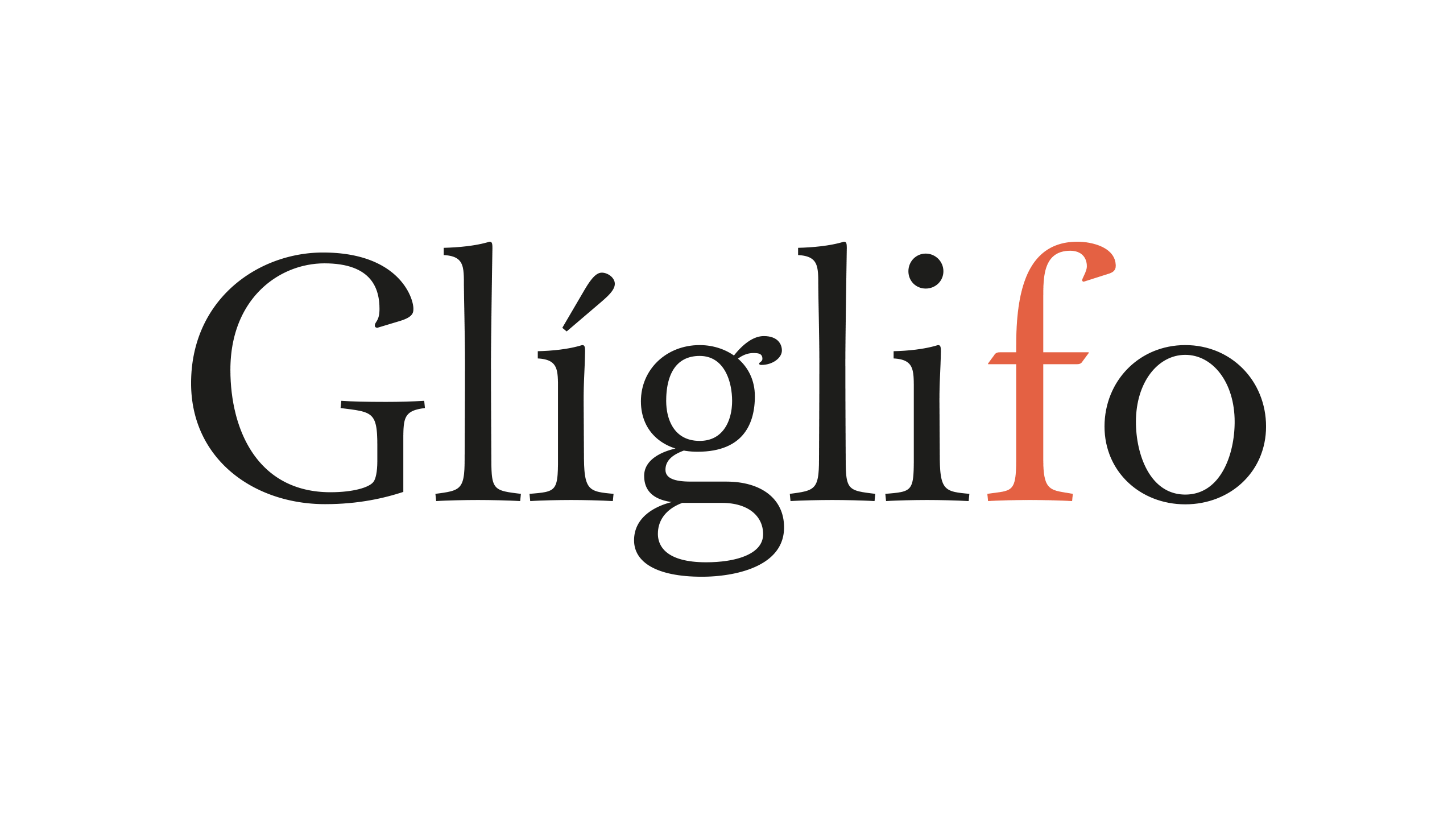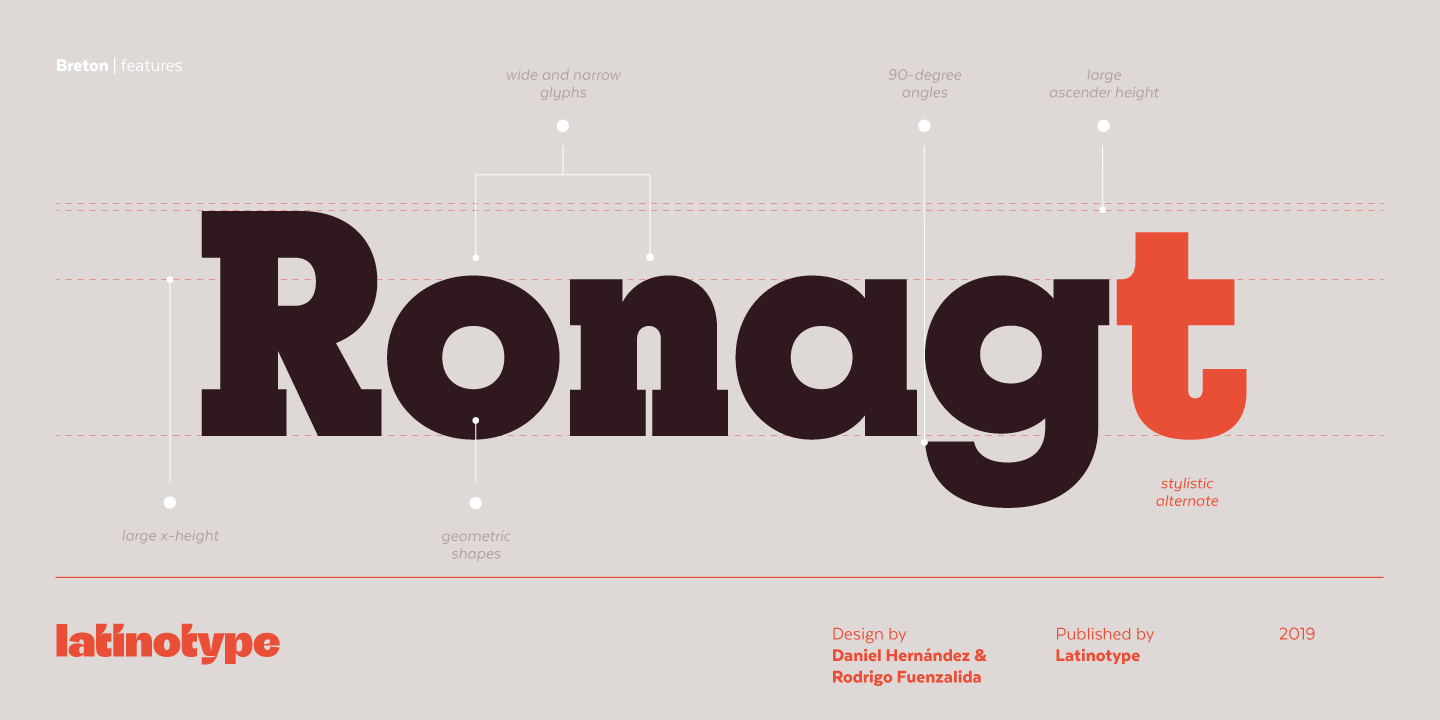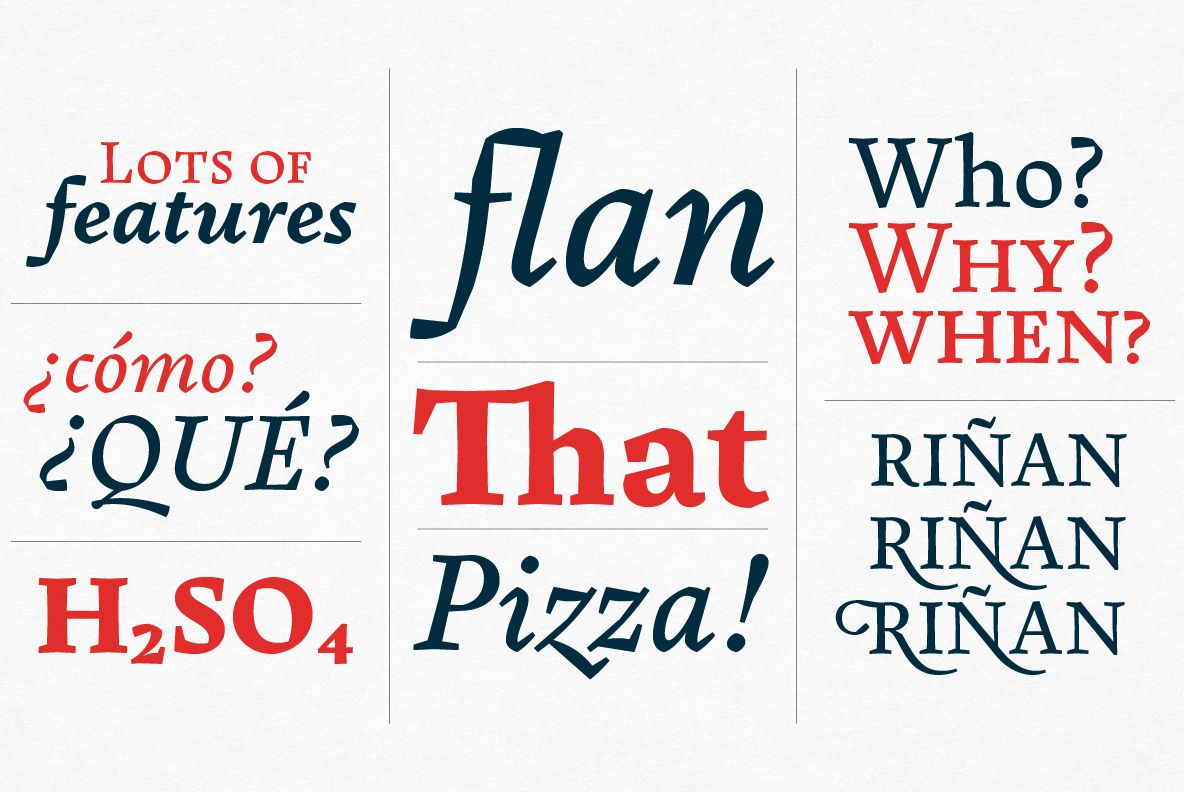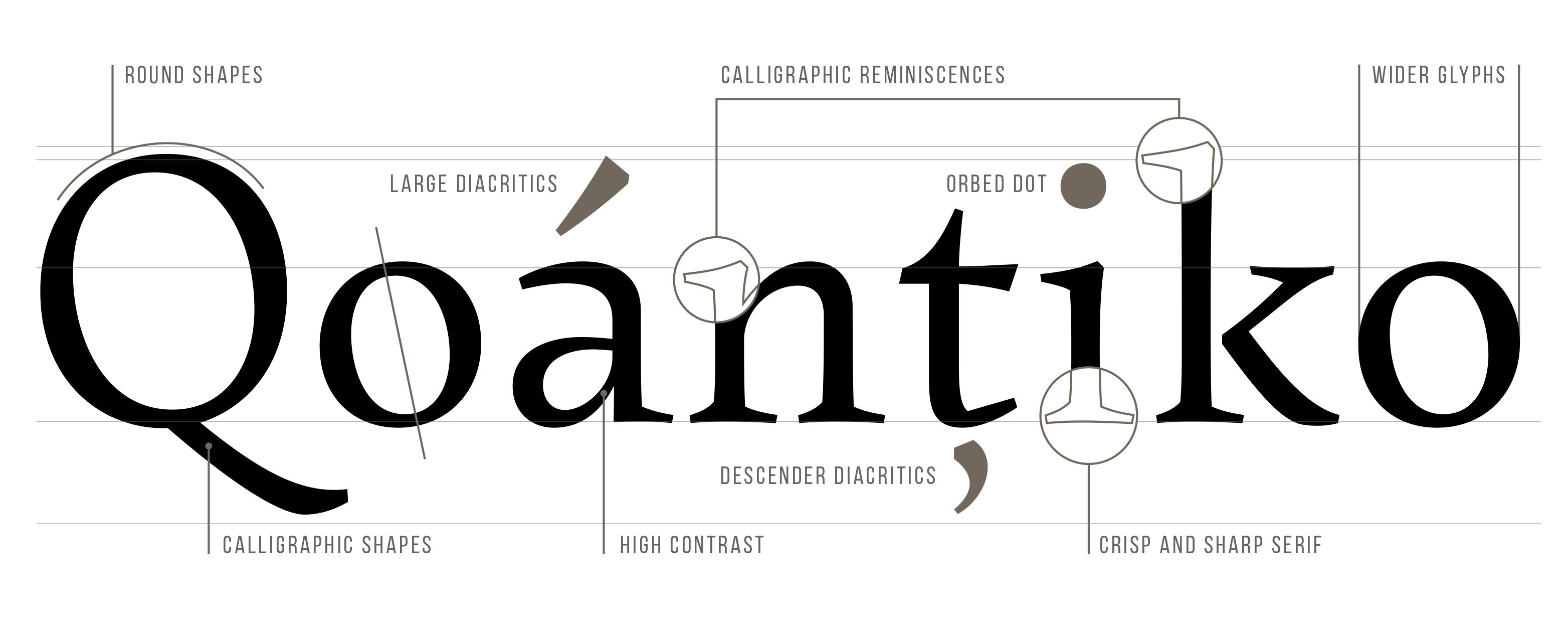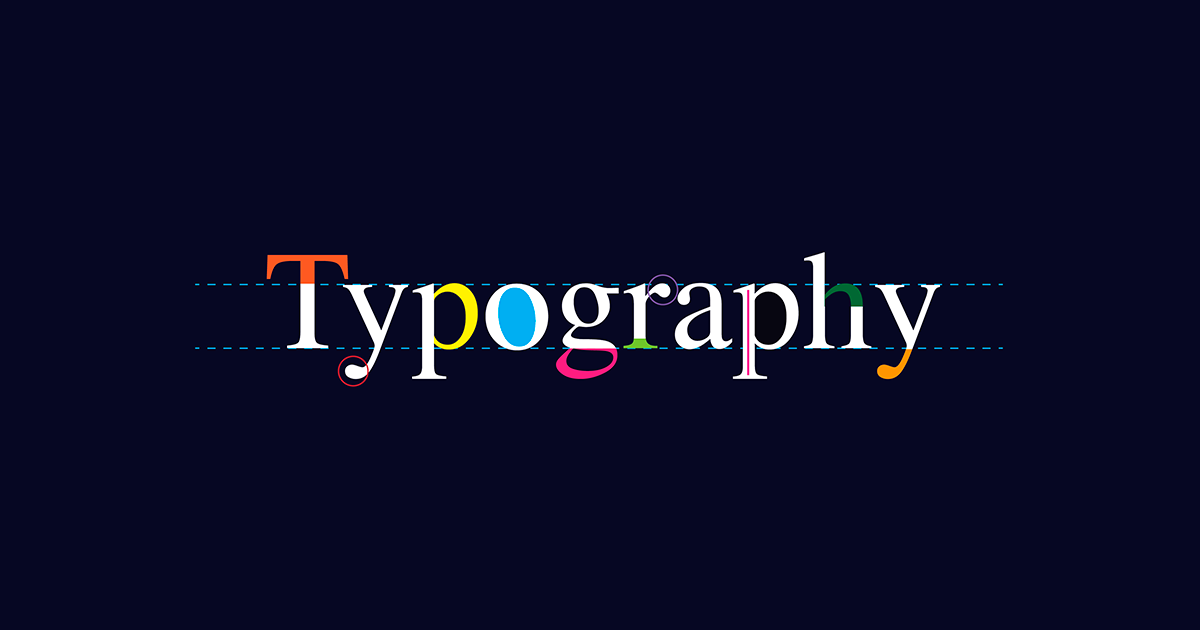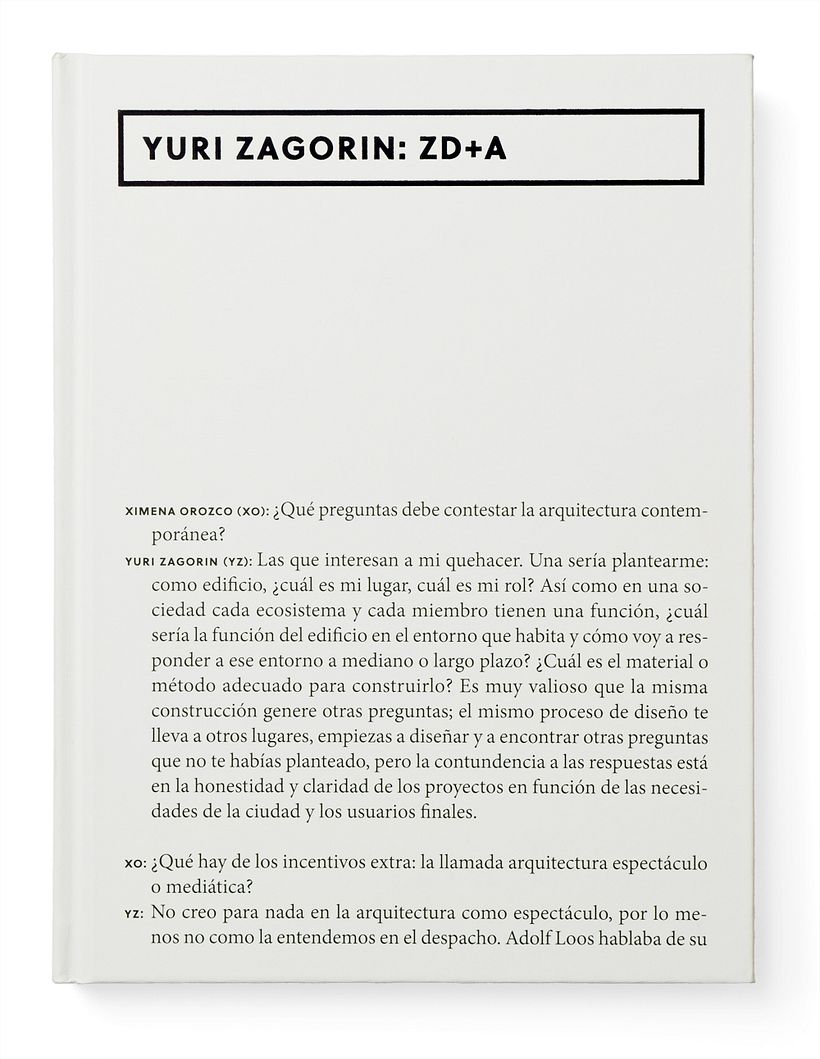
5 cursos esenciales para iniciarte en tipografía
Aprende todo sobre el diseño y la arquitectura de las palabras con estos grandes cursos de tipografía
El diseño busca comunicar, y algo que resulta elemental para ello es la combinación de estética y funcionalidad que puede proporcionar la tipografía. Diseñar tipografías es diseñar un conjunto de letras, números y signos que tienen características comunes, que se han creado bajo un mismo estilo: familias de caracteres cuyos miembros tienen rasgos comunes, pero que pueden estar sometidos a variaciones.
Para conocer, entender y visualizar de manera clara los atributos y características de la tipografía, existen ciertas habilidades que debes practicar y dominar, y son varios los profesionales que comparten su conocimiento y su experiencia para conseguirlas. Estos son 5 cursos que puedes encontrar en Domestika para adentrarte en las letras, los números y los signos:
Tipografía: construye tu palabra, un curso de Glíglifo
La tipografía es a la palabra escrita lo que el tono de voz es a cuando hablamos: crean atmósfera, estilo, reflejan o inducen estados anímicos, contribuyen activamente en la comunicación. Para ello, es importante conocer las bases teóricas de construcción y anatomía de la letra; en este curso las descubrirás, partiendo de formas básicas, y conocerás las leyes ópticas, teniendo en cuenta el espaciado, el ritmo y la legibilidad.
Principios básicos del diseño tipográfico, un curso de Latinotype
Más de medio siglo después de la invención de la imprenta moderna, el diseño de tipografías sigue siendo uno de los retos más desafiantes para un diseñador. En este curso aprenderás la anatomía del alfabeto latino y conceptos como la coherencia estilística, el ritmo, la forma, el espacio, las correcciones ópticas y las compensaciones visuales. También conocerás lo necesario para diseñar tu alfabeto modular y realizar una composición de palabras aplicando jerarquía, color y elementos visuales.
Diseño de una tipografía digital de la A a la Z, un curso de Juanjo López
Si lo que quieres es diseñar una tipografía usando Glyphs, Illustrator y OpenType, este curso es el indicado. Con él aprenderás los conceptos generales sobre el dibujo de letras y a manejar las curvas Bézier, a tener un sistema armónico de formas y espacios, a espaciar y hacer kerning, a mejorar la vista de tus tipos en pantalla con el hinting y, por supuesto, descubrirás consejos para comenzar una vida en torno al diseño tipográfico.
Microtipografía: fundamentos de composición tipográfica, un curso de David Kimura
Dentro del diseño tipográfico, es importante saber la importancia de una buena tipografía y la correcta elección de cada parámetro en los textos. Para ello, en este curso conocerás los conceptos básicos que todo diseñador debe tomar en cuenta antes de iniciar un proyecto editorial: la ortotipografía fundamental, las reglas básicas para espaciar correctamente los caracteres, la importancia del cuerpo, la interlínea, el ancho de caja y la justificación y, claro está, el proceso de composición de un texto.
Reinterpretación digital de tipografías clásicas, un curso de Oscar Guerrero
Conocer la historia de la tipografía es primordial. Estudiar las raíces de una fuente, sus caracteres, formas y manchas, te dará un mejor panorama de la evolución y claves para vislumbrar el futuro tipográfico. En este curso, conocerás más sobre la arqueología de las tipografías y analizarás sus características principales, aspectos estructurales y rasgos únicos para entender su ADN y generar una interpretación bien estructurada.